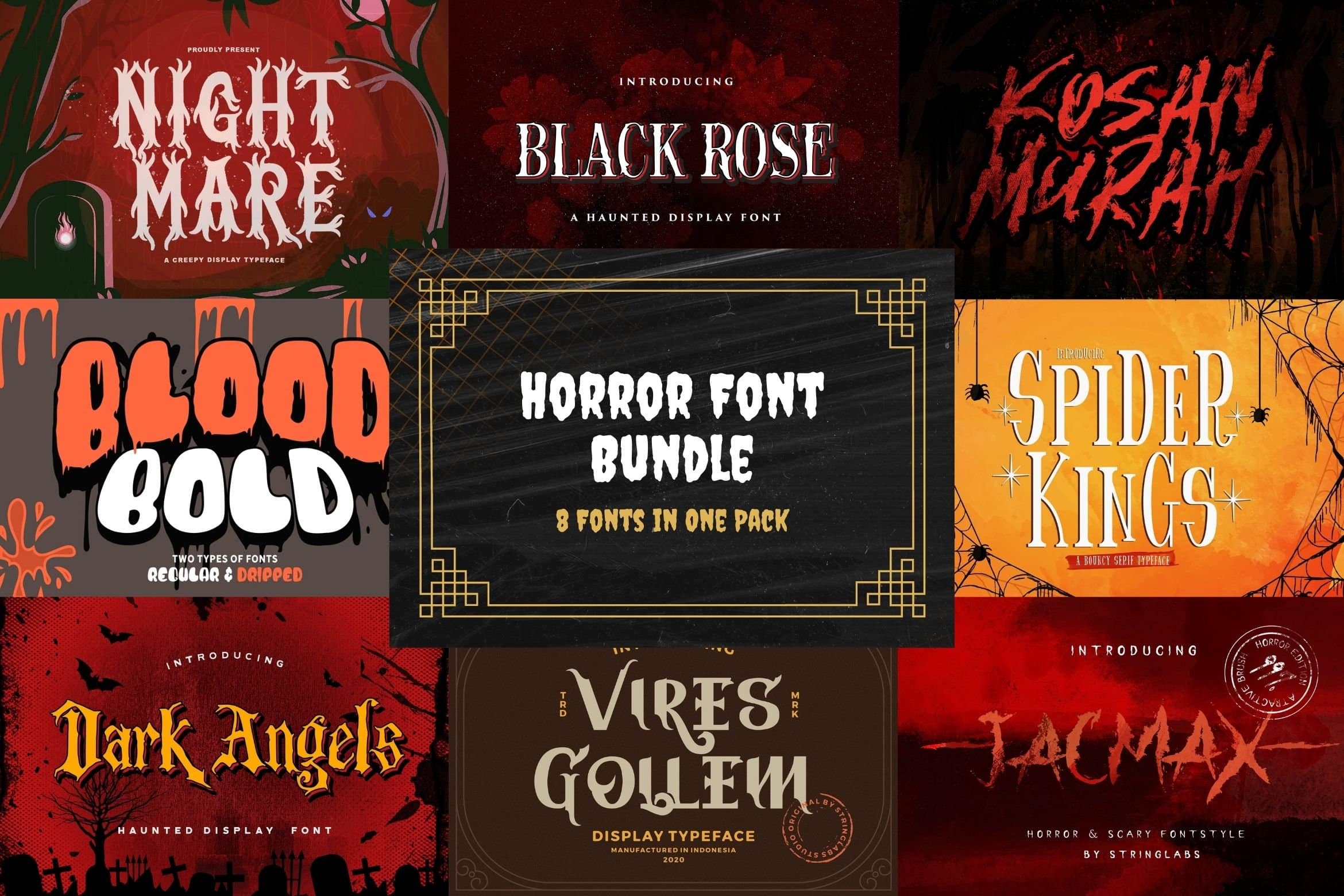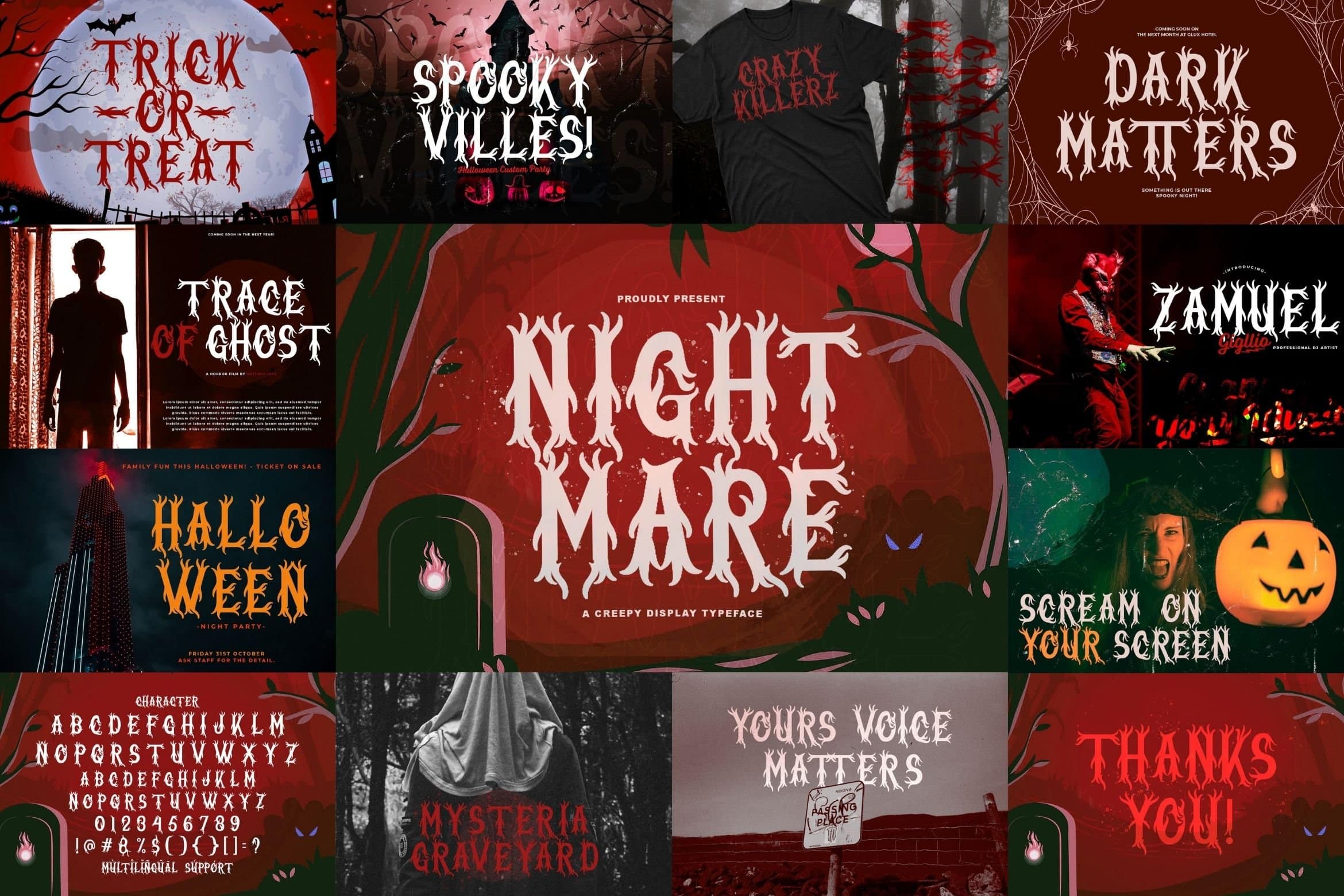
Mùa ma quái sắp đến rồi, đã đến lúc bạn nên chuẩn bị để có những thiết kế mang đậm không khí kinh dị và vui nhộn nhất cho Halloween năm nay! Dưới đây là danh sách 13 bộ ảnh, hình minh hoạ, clip art, và font chữ được tuyển chọn về Halloween mà bạn có thể tải về để mang lại một diện mạo mới đầy ám ảnh cho các dự án thiết kế của mình.
13 bộ ảnh và font chữ đặc biệt dành cho Halloween:
- Halloween Creepers Graphic Pack
- HORRORLAND Font
- Wednesday Addams Illustration
- Phantasm 12-Set Vintage Ghost Paintings
- 3D Cartoon-Style Halloween Vector File
- Spooky Night Halloween Clip Art
- Halloween Ghost Dog
- Halloween Characters Set Of Three Vectors
- Halloween Bottle & Potion Labels
- Vintage Collection of Halloween Characters & Decorations
- Horror Metal Font
- Sweet Halloween Font
- Horror Font Bundle
Halloween Creepers Graphic Pack
HORRORLAND Font
Bộ phông chữ vẽ tay cực ngầu này sẽ mang nét kinh dị cho các dự án sáng tạo của bạn, với ba biểu tượng bao gồm đầu lâu, trái tim và con dơi để tạo ra các tác phẩm vừa kỳ lạ vừa quyến rũ.
Wednesday Addams Illustration
Phantasm 12-Set Vintage Ghost Paintings
3D Cartoon-Style Halloween Vector File
Một số file vector dạng hoạt hình 3D cho Halloween.
Spooky Night Halloween Clip Art
Halloween Ghost Dog
Halloween Characters Set Of Three Vectors
Bộ 3 vector về các nhân vật Halloween vô cùng đáng yêu.
Halloween Bottle & Potion Labels
Một số mẫu thiết kế nhãn chai đầy ma quái.
Vintage Collection of Halloween Characters & Decorations
Bộ sưu tập ảnh các nhân vật và đồ trang trí Halloween theo phong cách cổ điển.
Horror Metal Font
Bộ phông chữ kinh dị mang phong cách nhạc metal.
Sweet Halloween Font
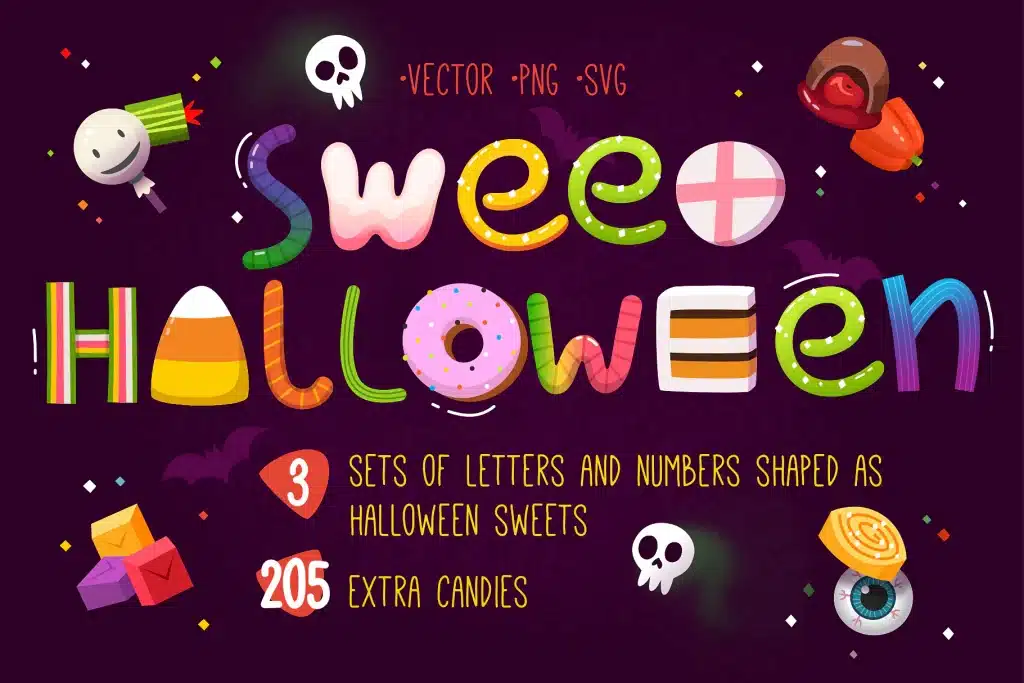
Bộ phông chữ Halloween nhưng với phong cách ngọt ngào kẹo bông.
Horror Font Bundle
Bộ sưu tập thú vị này có tận 8 phông chữ chất lượng cao đậm chất rùng rợn và gothic. Mỗi phông chữ mang đến phong cách và biến thể độc đáo riêng, khiến nó trở thành người bạn đồng hành lý tưởng cho nhiều dự án có vẻ ngoài độc ác, chẳng hạn như những áp phích phim khiến bạn lạnh sống lưng, những logo đầy ma mị hay những dòng chữ cho tiểu thuyết kinh dị.